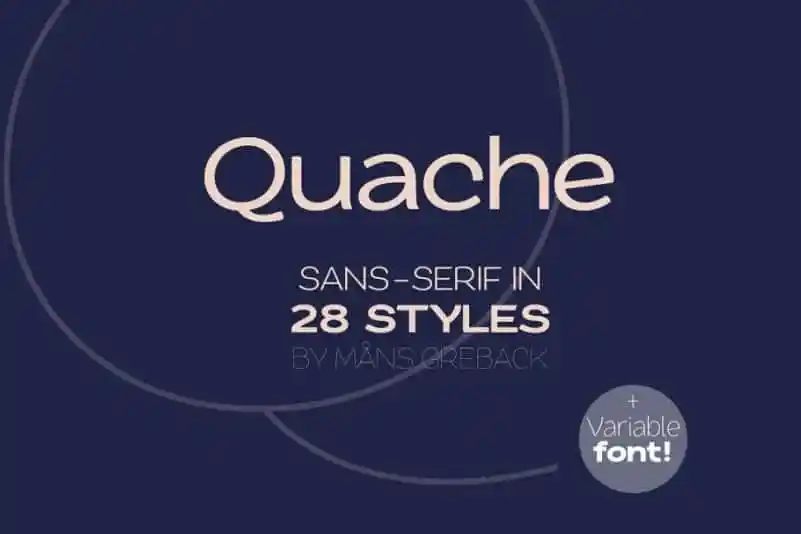
Convidamos você a conhecer uma nova fonte do tipo Sans Serif chamada Quache Sans Serif Font. Criada pelo designer sueco Måns Grebäck entre 2018 e 2020, esta fonte apresenta um estilo moderno e limpo com curvas elegantes que tornam a leitura fácil e confortável. Ideal para aplicações digitais e impressas onde o foco é a legibilidade e a clareza visual, a Quache Sans Serif não perde a presença no design, ao contrário, oferece uma forma aberta e sofisticada aos caracteres, tornando-a uma opção versátil e atrativa para diversos usos. Seja você um designer gráfico, web designer ou editor de arte digital, a Quache Sans Serif será um aliado valioso em sua paleta de fontes.